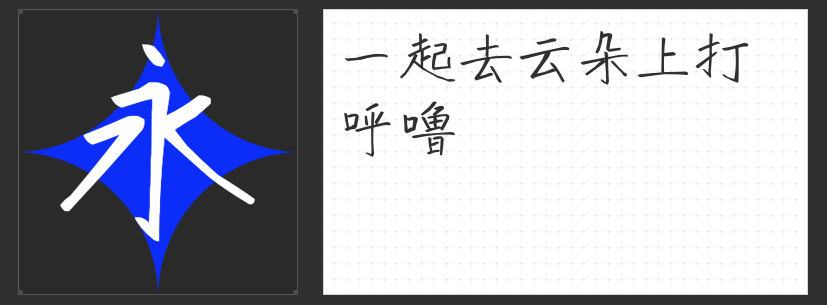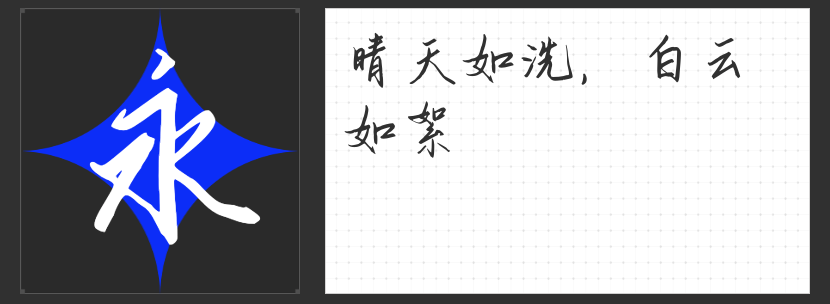
手写字体设计指南:四款风格化字库解锁创意表达新维度
在数字设计趋同化的今天,手写字体的温度与个性成为品牌突围的关键。从传统书法的写意到现代审美的灵动,以下四款风格迥异的手写字库,以独特的笔触语言为设计注入人文气息,满足从商业品牌到艺术创作的多元需求。
一、小豆岛默陌枝桠简
这款字体以“破而后立”的设计哲学重构水墨意境,通过运笔节奏的强弱对比塑造线条粗细,在疏密有致的布局中暗藏枯枝藤蔓的张力。笔画转折处刻意保留的飞白效果,既延续了传统书法的写意精神,又以抽象化的视觉语言适配现代设计场景。尤其适合茶饮、文创等强调文化底蕴的品牌主视觉,或作为书籍封面标题传递禅意哲思。
二、字青春悸动简 常规
以端正字形为基底,通过微妙的笔画弧度变化打破僵直感,在清秀别致中暗藏灵动气息。这款字体的设计精髓在于“克制中的变化”——横画起笔的轻顿、竖画收尾的回锋,既保证远距离识别的清晰度,又通过细节处理营造手写温度。短视频字幕、校园活动海报等年轻化场景中,其恰到好处的活泼感能有效拉近与受众的距离。
三、MyFont冲鸭简繁
瘦长字身与右上方微倾的态势构成视觉动线,纤细笔画中暗藏力量感,如同破土而出的新芽。设计师通过字面大小的自然波动与笔画伸张的节奏控制,让文字仿佛自带呼吸韵律。这款字体尤其适合运动品牌、儿童产品等需要传递活力感的领域,在社交媒体表情包、动态海报设计中更能凸显其轻盈特质。
四、MyFont晴天楷简繁
以硬笔书写为根基,在结体规整中融入行草的洒脱,主笔画出锋时的果断笔触如同阳光穿透云层。这款字体的突破性在于打破楷书刻板印象,通过适度倾斜的横画与舒展的捺脚构建开放字腔,既保持正式文件的易读性,又能为品牌包装、书籍装帧注入清新气质。其“刚柔并济”的特性,使其成为全场景设计的安全牌。
从水墨写意到硬笔锋芒,这四款字体以不同的手写逻辑诠释文字的温度。